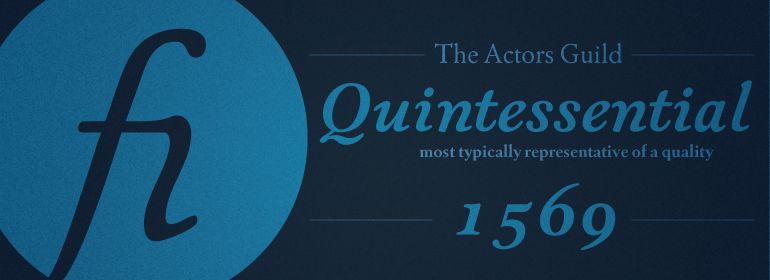
ITC New Winchester™
ITC New Winchester™,这款字体结构工整、笔画清晰,兼顾美观与易读性,适用于标题、正文、海报、包装、LOGO 等多种场景。字形优雅稳定,风格百搭耐看,适配日常排版与创意设计,让文字呈现更舒适、更具质感。ITC New Winchester™一笔一画,皆是细节,以均衡的比例、流畅的线条打造舒适视觉体验,字形端正大气,风格简约现代。无论是商业设计、品牌宣传还是日常排版,都能轻松驾驭,让文字更有格调与力量。ITC New Winchester™字体下载。
ITC New Winchester是从未真正发布过的字体的复兴。最初的温彻斯特(Winchester)是由美国字体设计师W.A. Dwiggins于1944年创建的实验设计。Dwiggins希望通过减少上乘和下乘的数量来提高英语的可读性。为此,他给了温彻斯特很短的后代,并为许多字母创建了不正当的形式。结果是一种独特的文字字体,Dwiggins和Dorothy Abbe偶尔以手机形式使用。五十年后,印第安纳州字体设计师Jim Spiece将Dwiggins的实验变成了一个新的数字文本类型家族。斯伯特(Spiece)给新温彻斯特(New Winchester)带来了大胆的重量,以及小写的字体(包括罗马字体和斜体字体)和旧样式。他还创建了两种形式的小写字母f,一种带有和不带有悬垂的小写字母(在金属类型中为kern),以及一组完整的f-连字。
ITC New Winchester is a revival of a typeface that never really had a first release. The original Winchester was an experimental design created by the American type designer W.A. Dwiggins in 1944. Dwiggins was interested in improving the legibility of the English language by reducing the number of ascenders and descenders; to do this, he gave Winchester very short descenders and created uncial forms for a number of letters. The result was a distinctive text typeface that was occasionally used by Dwiggins and Dorothy Abbe in handset form. Fifty years later, Indiana type designer Jim Spiece has turned Dwiggins's experiment into a new family of digital text types. Spiece gave New Winchester a bold weight, as well as small caps (both roman and italic) and old style figures; he also created two forms of the lowercase f, one with and one without an overhang (in metal type, a kern), and a full set of f-ligatures.